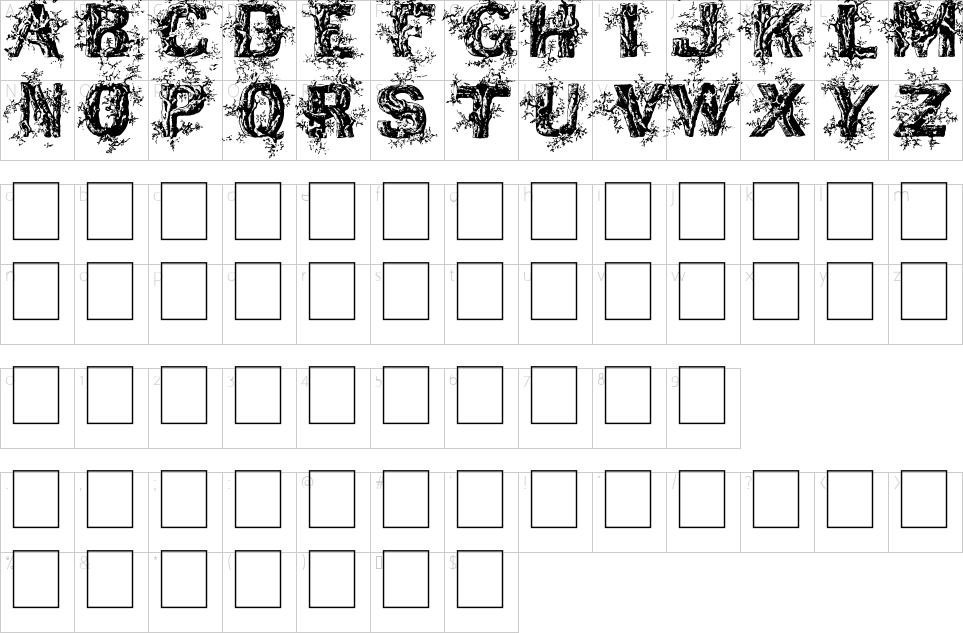
A fonte Deep Woods é uma escolha perfeita para designers buscando uma face natural e envolvente. Desenvolvida por Paul Lloyd, essa fonte é perfeitamente adaptada para a criação de designs naturais, paisagistas, ilustrações e até mesmo para o design gráfico de sites e aplicativos. Com uma paleta de cores suave e linhas elegantes, Deep Woods oferece um aspecto profundo e natural que combina perfeitamente com estilos como gráficos minimalistas e artesanato de estilo selvagem. Com seu design cuidadosamente cuidado, é uma ótima opção para criar uma atmosfera de tranquilidade e harmonia, que se alinha perfeitamente com o conceito de Deep Woods. Esta fonte, disponível tanto para Windows quanto para Mac, foi baixada mais de 12.041 vezes, testemunhando seu reconhecimento e popularidade entre os designers. Se você está buscando uma fonte que pode complementar e dar vida a seus projetos, Deep Woods é uma escolha atraente para considerar.